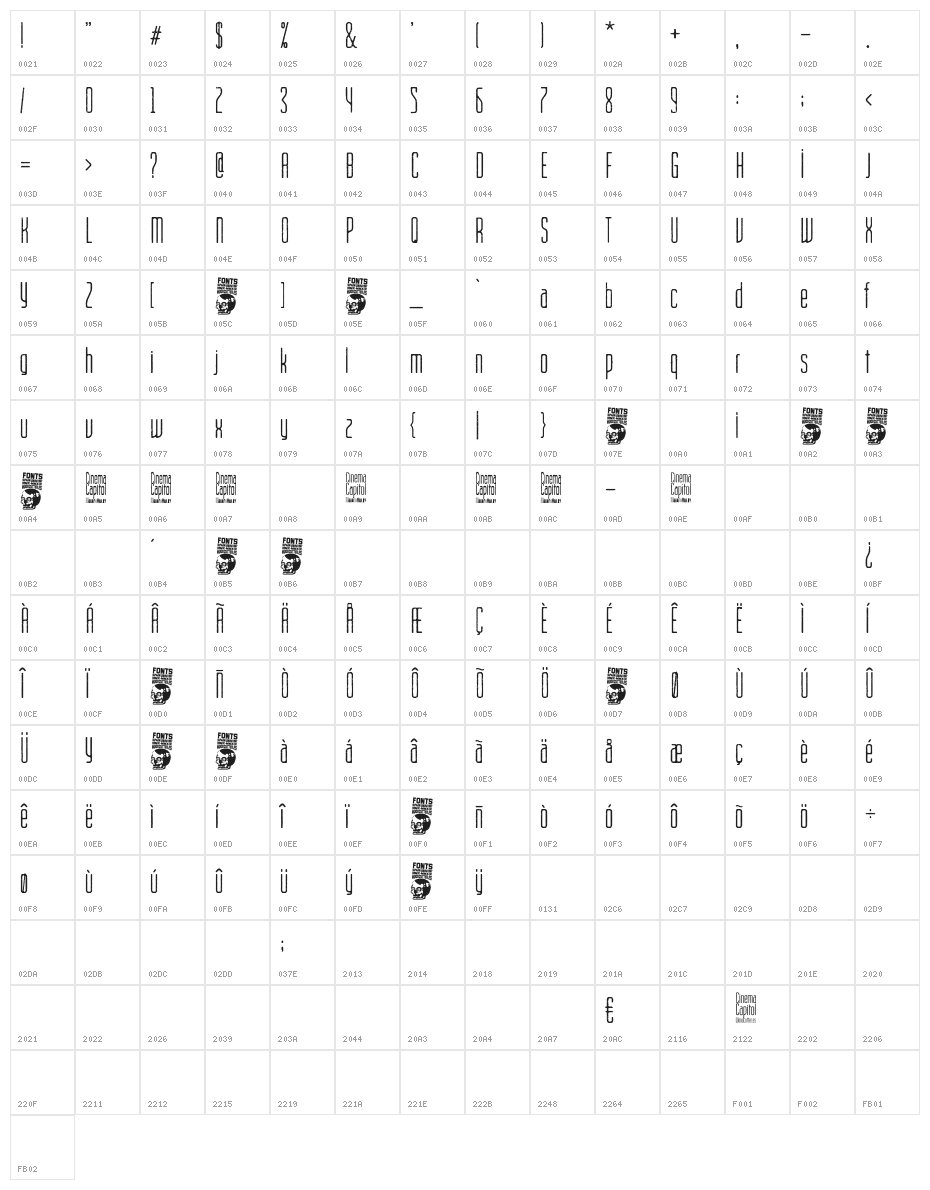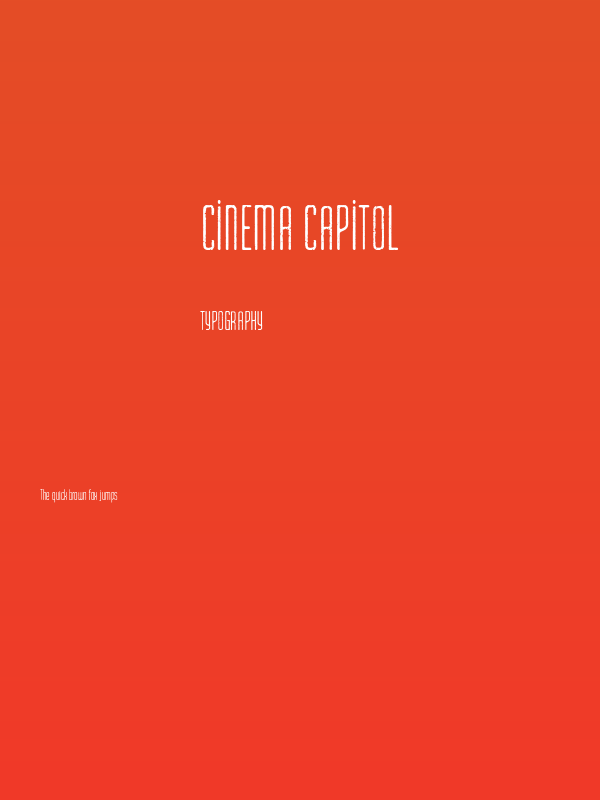
Cinema Capitol Font
| Gesamtstil | Vintage |
| Vorgeschlagene Projekte | Ideal for vintage-themed posters, retro branding, theater signage, and nostalgic design projects. |